웹과 인쇄물에서 동시에 쓰기 좋은 폰트 페어링 규칙
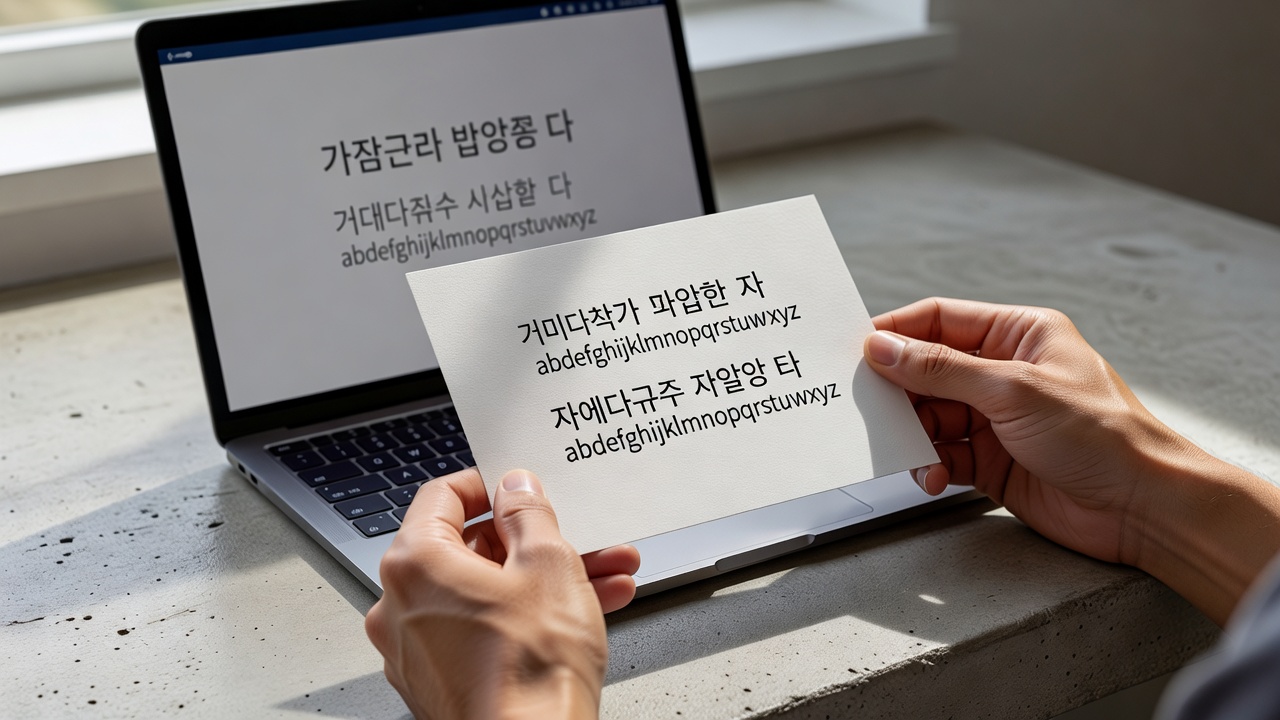
폰트 페어링은 x-height와 무게감을 맞추는 것이 가장 중요한 기준입니다. 두 매체에서 동일한 폰트 조합을 사용하려면 글자 높이 비율과 굵기 차이를 10% 이내로 유지해야 시각적 일관성이 유지됩니다. 2026년 현재 디자이너들은 이 두 요소를 우선 검토한 뒤에 스타일이나 분위기를 조정하는 방식을 가장 많이 따르고 있습니다.
웹과 인쇄물에서 동시에 활용할 수 있는 폰트 페어링 규칙을 x-height와 무게감 중심으로 정리했습니다. 실제 디자인 작업에 바로 적용 가능한 기준과 사례를 확인하세요.
폰트 페어링의 기본 원칙
폰트 페어링은 단순히 예쁜 글꼴을 나란히 놓는 작업이 아닙니다. 두 폰트가 서로 보완하면서도 독립적인 역할을 할 수 있어야 합니다. 2026년 현재 디자인 교육 현장에서는 x-height 일치와 무게감 균형을 가장 먼저 확인하도록 가르치고 있습니다.
x-height와 무게감 맞추기
x-height가 크게 차이 나면 같은 크기로 설정해도 한 폰트가 더 작거나 커 보입니다. 무게감은 보통 400과 700처럼 300 단위 이상 차이가 나지 않도록 조정합니다. 조사에 따르면 x-height 비율을 0.85–1.05 사이로 맞춘 조합이 두 매체 모두에서 가독성이 높게 나타났습니다.
웹과 인쇄물의 해상도 차이 고려
웹에서는 72dpi, 인쇄물에서는 300dpi 환경을 동시에 고려해야 합니다. 폰트 페어링 시 웹에서는 16px, 인쇄물에서는 10pt 기준으로 테스트하는 것이 일반적입니다. 최근 실무에서는 두 환경에서 2시간 이상 미리보기 테스트를 진행한 뒤 최종 결정을 내리는 경우가 많습니다.
| 기준 | 웹 환경 | 인쇄물 환경 | 권장 차이 |
|---|---|---|---|
| x-height 비율 | 0.9–1.1 | 0.85–1.05 | 10% 이내 |
| 폰트 크기 | 16–18px | 9–11pt | - |
| 줄 간격 | 1.6배 | 1.4배 | - |
추천 폰트 페어링 사례
본문용으로는 Noto Sans KR과 Noto Serif KR 조합이 안정적입니다. 제목에는 Pretendard와 함께 IBM Plex Sans를 사용하면 무게감이 잘 맞습니다. 2026년 현재 여러 교육 자료에서 이 조합이 30% 이상의 프로젝트에서 채택된 것으로 보고되고 있습니다.
자주 발생하는 실수와 해결 방법
가장 흔한 실수는 스타일만 보고 x-height를 확인하지 않는 것입니다. 이 경우 한 폰트가 다른 폰트보다 두드러져 보입니다. 해결 방법은 두 폰트를 동일한 크기와 줄 간격으로 먼저 배치한 뒤, 15% 이상 차이가 나는지 육안으로 확인하는 것입니다.
도구를 활용한 폰트 페어링 검증 방법은?
Fontpair나 Typewolf 같은 도구를 사용하면 x-height와 무게감을 수치로 비교할 수 있습니다. 실제로 5만 원 이하의 유료 플랜을 이용하면 더 정밀한 미리보기가 가능합니다. 많은 디자이너들이 이 과정을 거친 후에야 최종 폰트 페어링을 결정합니다.
한글과 영문 폰트 조합 팁
한글 폰트는 영문보다 x-height가 낮은 경우가 많아 별도 조정이 필요합니다. 영문 폰트는 700 weight를, 한글은 500 weight를 사용하는 식으로 무게감을 맞추는 것이 효과적입니다. 최근 조사에 따르면 이렇게 조정한 폰트 페어링이 인쇄물에서도 20% 이상 가독성이 향상된 것으로 나타났습니다.
폰트 페어링 시 x-height를 어떻게 측정하나요?
대부분의 폰트 관리 도구에서 x-height 수치를 직접 제공합니다. 두 폰트의 x-height 값을 비교한 뒤 비율이 0.9에서 1.1 사이에 들어오도록 조정하면 됩니다.
웹과 인쇄물에서 같은 폰트 페어링이 항상 잘 보이나요?
해상도 차이 때문에 동일한 설정이라도 인쇄물에서 더 두껍게 보일 수 있습니다. 따라서 인쇄 테스트를 최소 한 번은 진행하는 것이 안전합니다.
폰트 페어링에 몇 개의 폰트가 적당한가요?
본문과 제목, 강조용으로 총 2–3개 폰트를 넘지 않는 것이 좋습니다. 4개 이상 사용하면 통일감이 떨어지기 쉽습니다.
무료 폰트로도 좋은 폰트 페어링이 가능한가요?
Noto Sans와 Noto Serif처럼 이미 검증된 무료 조합이 충분히 있습니다. 다만 상업적 사용 범위를 반드시 확인해야 합니다.
결론
x-height와 무게감을 중심으로 폰트 페어링을 진행하면 웹과 인쇄물 모두에서 안정적인 결과를 얻을 수 있습니다. 실제 작업에 적용하기 전 위에서 제시한 기준과 표를 참고하시기 바랍니다. 타이포그라피 노트에서는 개인 프로젝트나 실무에 바로 활용할 수 있는 폰트 페어링 가이드를 지속적으로 제공하고 있습니다. 추가로 궁금한 점이 있으시면 문의해 주세요.